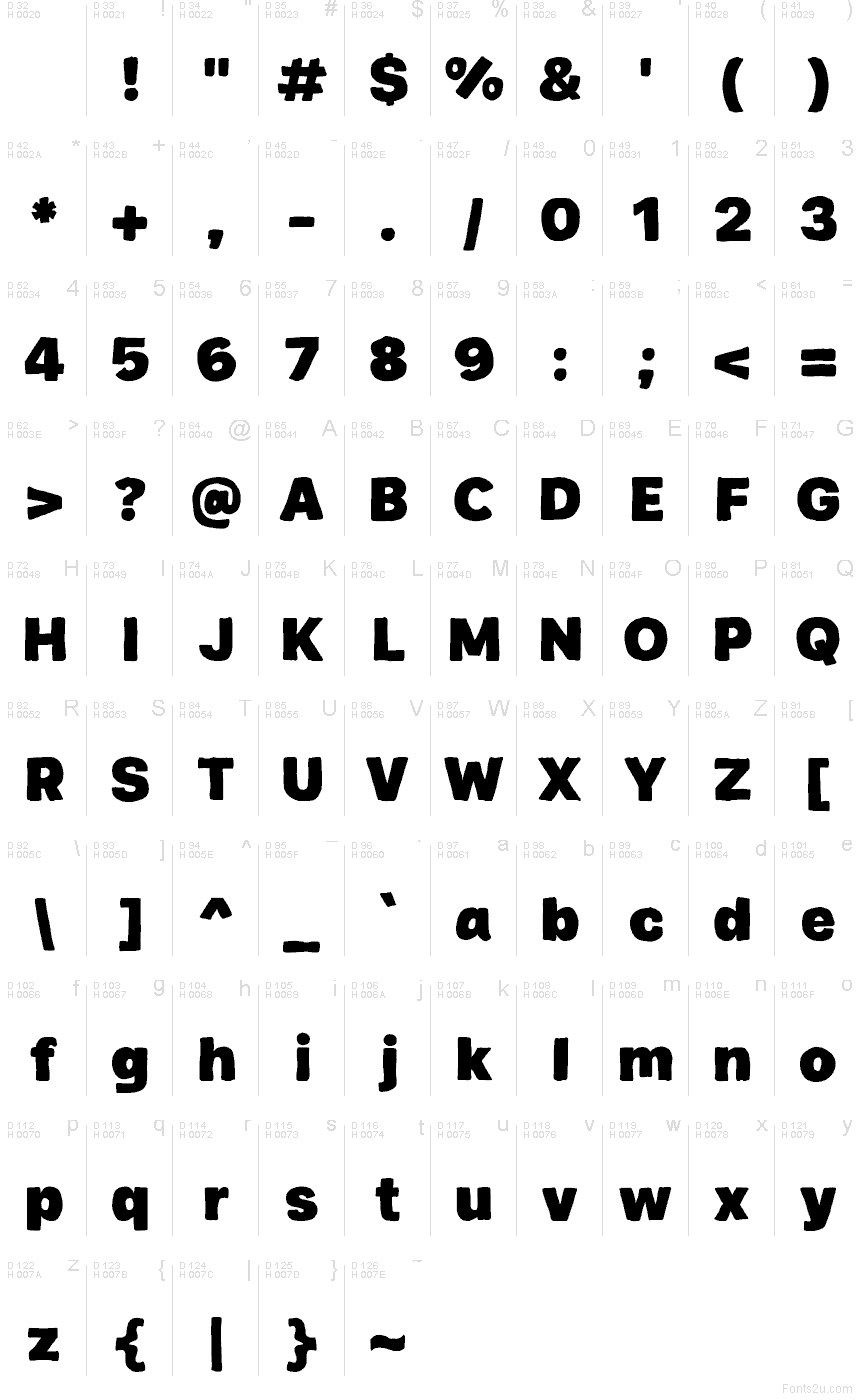
Vintage Vibes
Vintage Vibes od MJType je bezplatné erodované písmo typu display so zaoblenými tvarmi a nepravidelnými, zvetranými okrajmi. Písmená pôsobia mäkko a plne, ale opotrebované výrezy a drsné obrysy im dodávajú charakter autentického tlačeného vzhľadu.
Vintage Vibes sa skvele hodí na titulky plagátov, obaly albumov, vintage balenia, letáky k akciám, logá značiek a nápisy, ktoré potrebujú zostarnutý finiš. Toto bezplatné písmo prináša ručne vytvorenú textúru, ktorá je ideálna pre návrhy s vyblednutým vzhľadom s nádychom histórie bez toho, aby pôsobilo príliš rušivo.